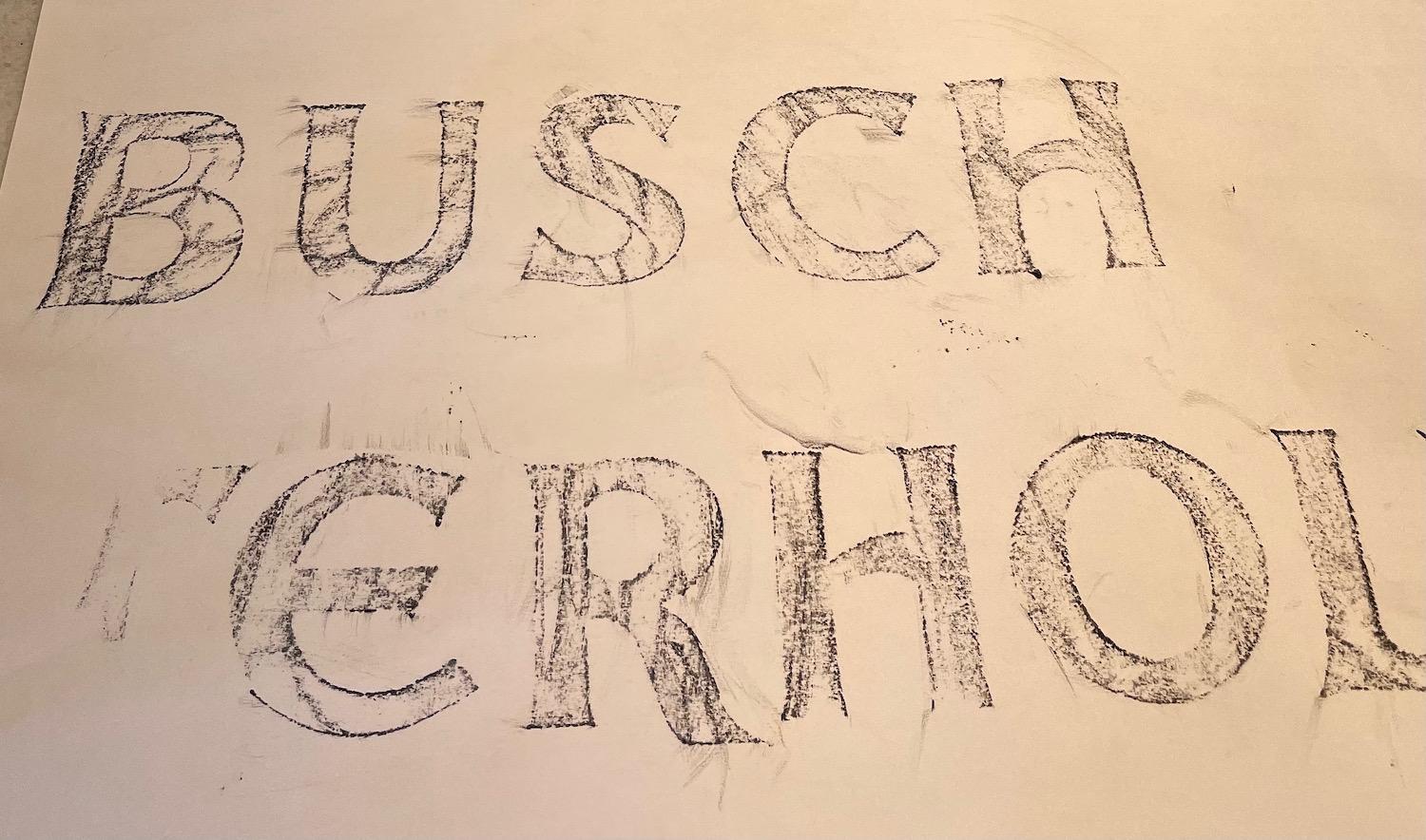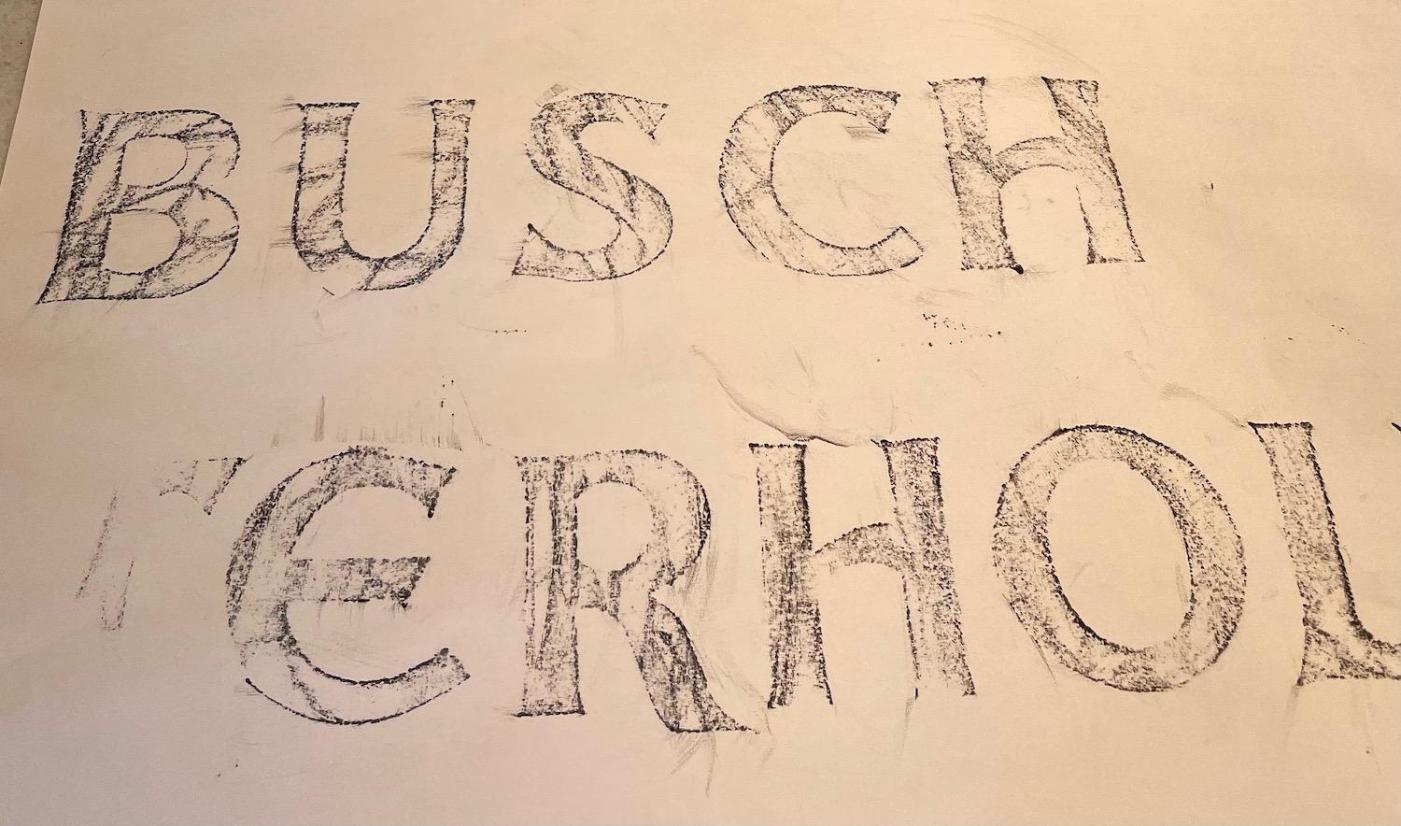
Schrift auf Grabstein "erneuern"
bisher habe ich nur still mitgelesen, jetzt wende ich mich mit einer Frage nach einer Schrift an euch. Ein Verwandter möchte einen Familiengrabstein neu gestalten lassen und im Zuge dessen auch die alte Schrift - hier im Bild als Frottage - durch eine Ähnliche ersetzen, bei der das "e" weniger an das Euro-Zeichen erinnert - eine Assioziation die ja nun wirklich nicht zu einem Grabstein passt. Hat jemand einen Vorschlag oder kennt vielleicht sogar einen Namen für Schriften dieser Art?
Dieses Є ist einigermaßen üblich bei Grabsteinen, ein € wird hier vermutlich nicht darin gesehen.
Ich würde einen pragmatischeren Weg gehen und den Steinmetz fragen, welche Schrift er gravieren kann oder – falls Maschinengravur – welche Schriftarten in der Maschine installiert sind. Unter der Prämisse, kein dem € ähnliches E zu verwenden. Anregungen gibt es genügend im www, auch Beispiele, wie ein Є gut aussehen kann.
@Calito: An den Serifen sind die Schriften wirklich sehr ähnlich. Die Friz scheint mir auch gut zu einem Grabstein zu passen. Persönlich ist sie mir zu "streng". Danke für den Vorschlag, den ich weiterreichen werde.
@Ralf: Ca. 10 Jahre. Über den Ursprung ist mir leider nichts bekannt.
@Weiß: Dass Grabsteinen mit Maschinen mit "installierten" Fonts graviert werden, kam mir noch gar nicht in den Sinn. Aber vor dem Hintergrund ist Rückgriff auf eine der gegebenen Schriften natürlich der angeratenste Weg. Magst du mir noch den Name des Fonts aus deinem Beispiel geben?
Das Beispiel stammt von hier, ein Name ist nicht angegeben.